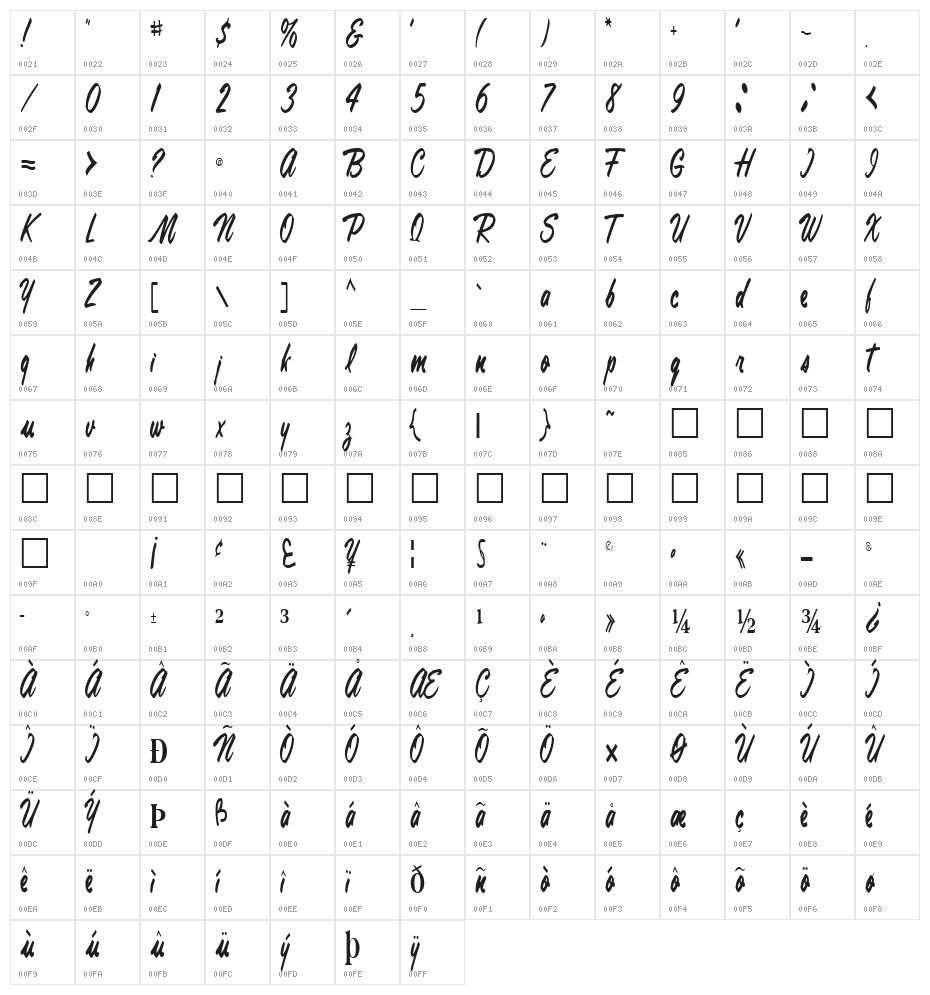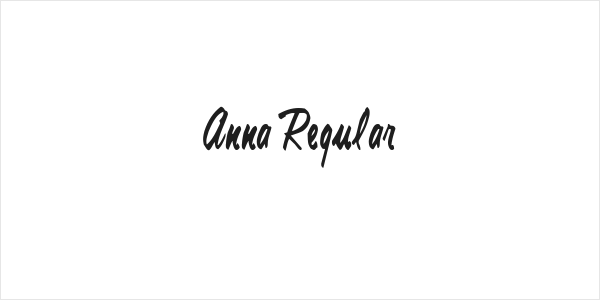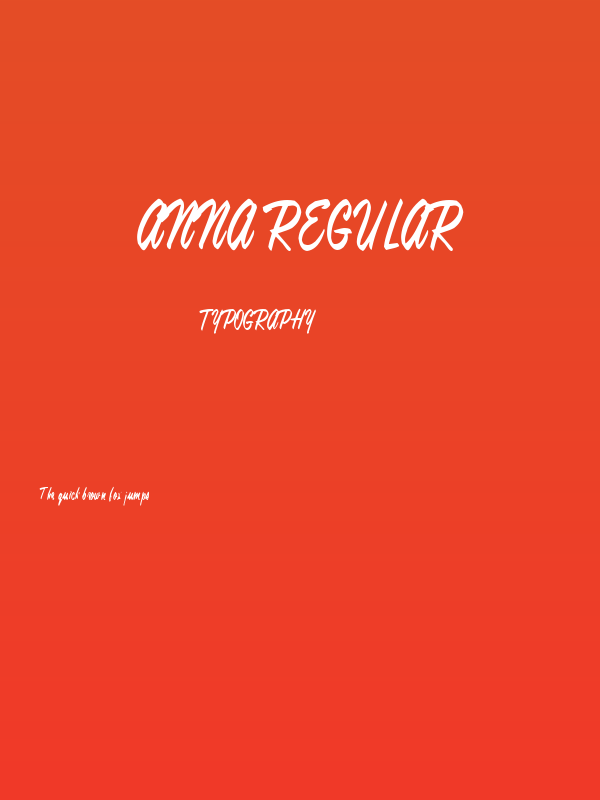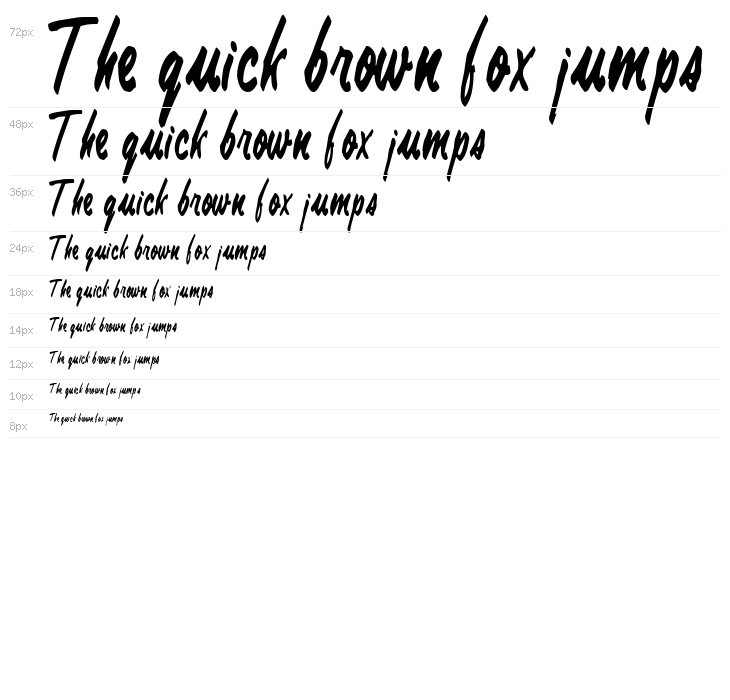
Anna Regular Font
| Categorie | 50s |
| Caso d'uso | Logos, Invitations, Artistic projects |
| Progetti proposti | Ideal for wedding invitations, greeting cards, logos, and branding projects that require a personal touch. |